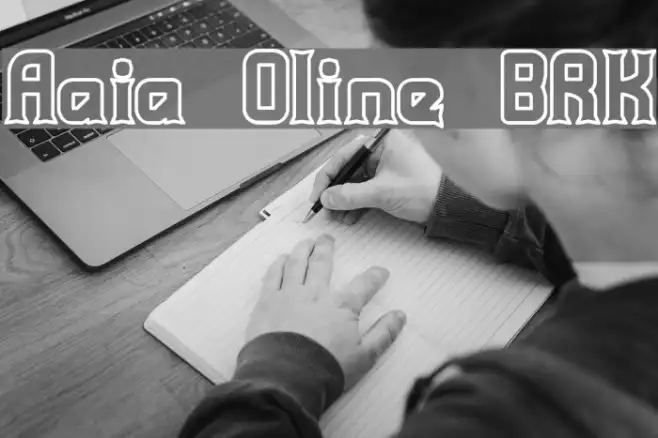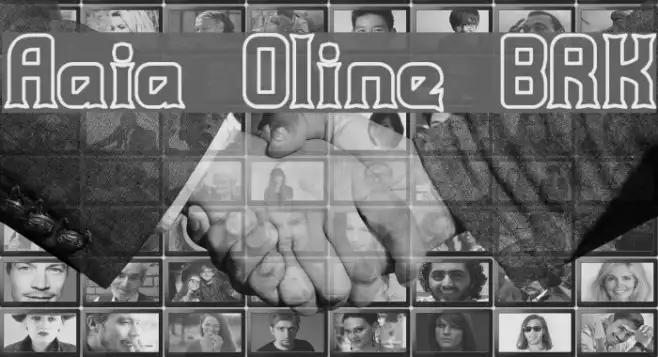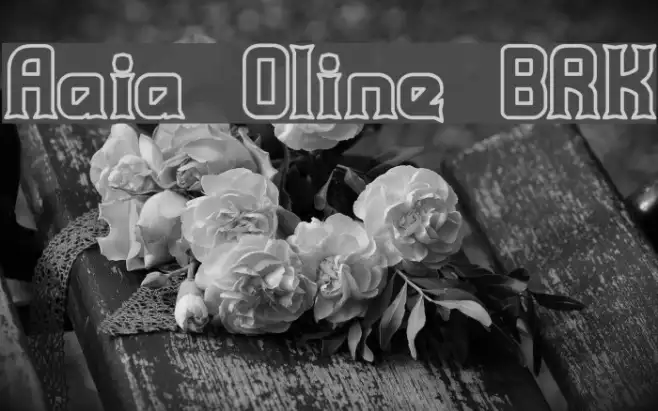
Ataxia Outline [BRK] Font
| Vorgeschlagene Projekte | Ideal for posters, logos, video game graphics, and any project needing a bold, standout typeface. |